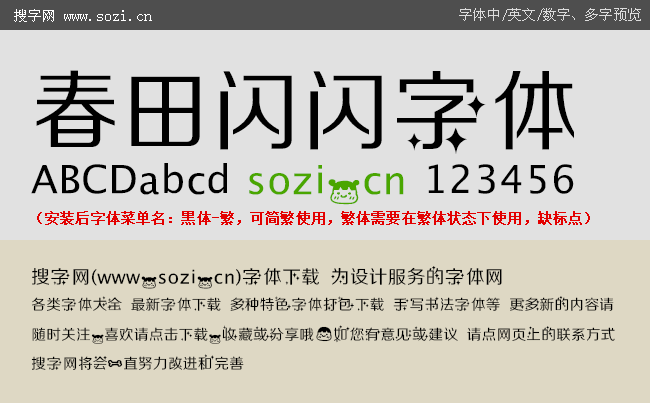
春田閃閃字體
搜字網(wǎng)給大家提供一款很有趣的手機(jī)中文字體下載。字體名字叫春田閃閃字體,這款手機(jī)字體是以正黑體為原形,在字體間加入了卡通圖案進(jìn)行裝飾,使字體在具有端正易認(rèn)的同時(shí)具有趣味性。特別適合喜歡手機(jī)字體個(gè)性一些的朋友在手機(jī)上安裝使用。